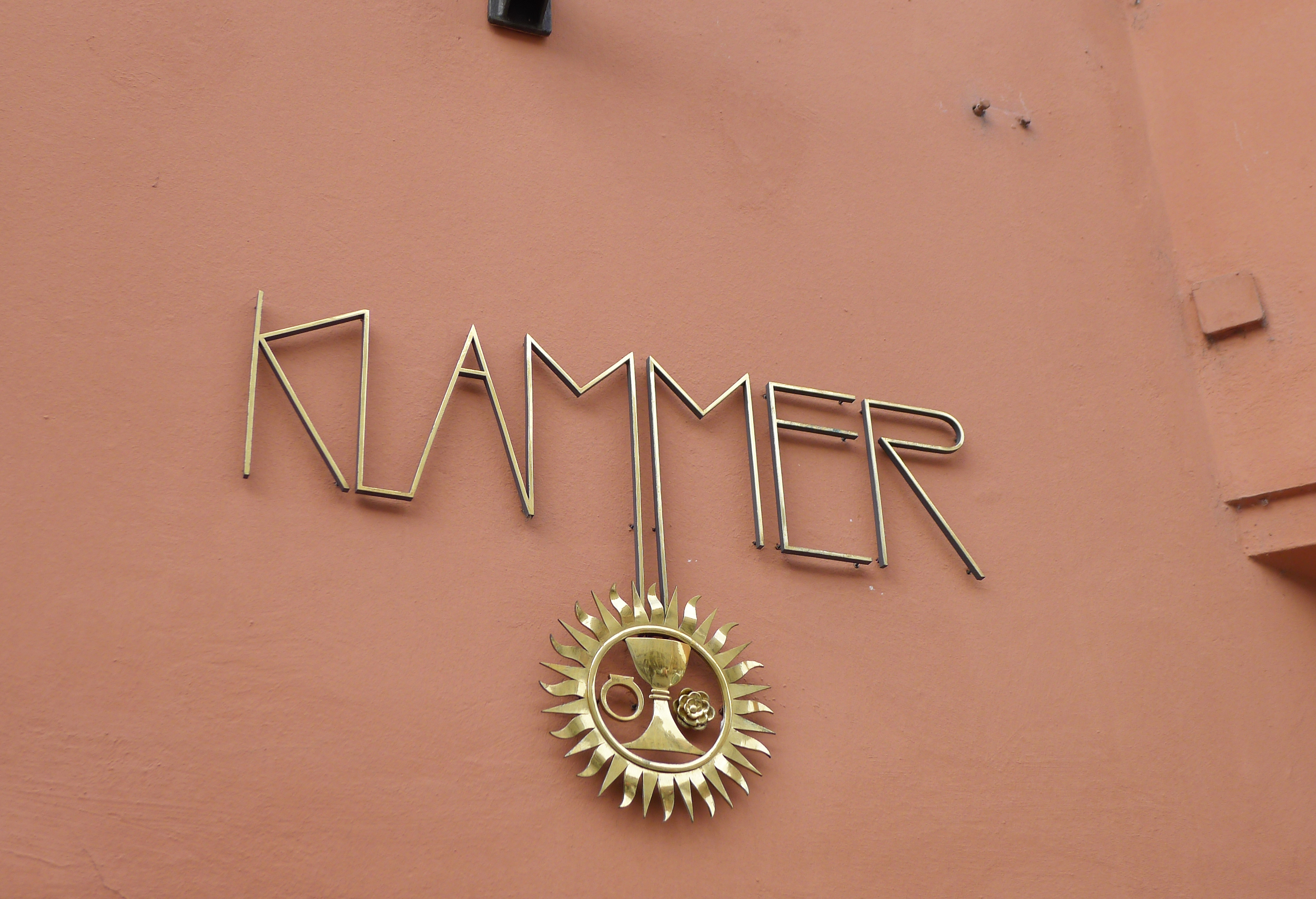
Juwelier-Klammer
Für den Juwelier Klammer setzt der 2001 verstorbene Tiroler Gestalter Arthur Zelger eine extra dünne, jugenstil-inspirierte und dennoch konstruierte Groteskschrift ein. Nobel, elegant, stilvoll – das soll diese Schrift sagen. In der nächsten Umgebung finden sich weitere Schriftzüge Zelgers, der mit seiner „Handschrift“ die Innsbrucker Innenstadt nicht unwesentlich prägte: Frechinger, Putzenbacher, Café Central, Held, Friseur Stummer, Walde uvm.
Innsbruck, Maria-Theresienstraße